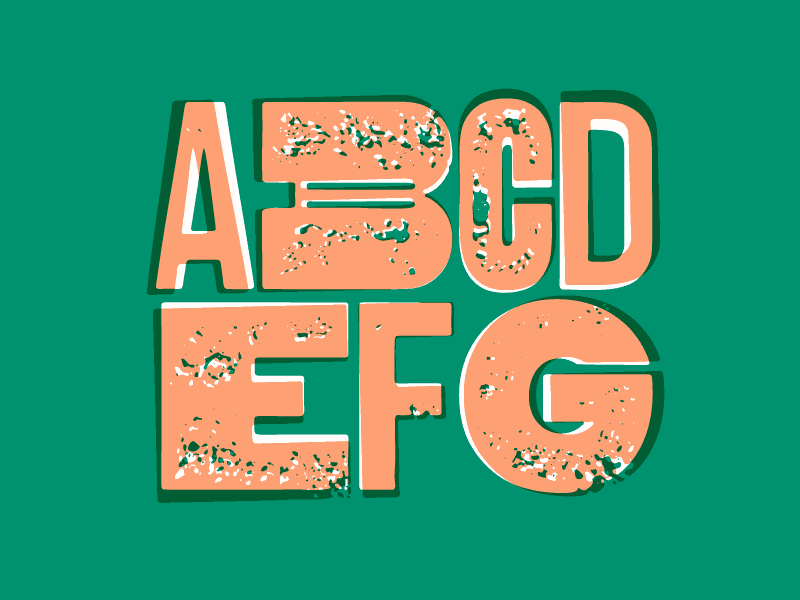
O písme
Písmový systém inšpirovaný drevenými matricami a drevotlačou.
Woodkit Reprint je kapitálové, dekoratívne, experimentálne konštruované písmo primárne určené pre použitie v nadpisoch, obsahujúc 6 štýlov.
Podporovanými znakovými sadami písma Woodkit Reprint sú základná latinka, rozšírená latinka, cyrilika a gréčtina, vďaka čomu môže byť písmo použité vo viac ako 109 jazykoch. S celkovým počtom 1150 znakov, základnou sadou sú tabulárne zarovnané číslice doplnené o proporčné zarovnané číslice a proporčné skákavé číslice pre pokročilú numerickú sadzbu. Funkcie ako štandardné ligatúry, špeciálne ligatúry a kontextové varianty umožňujú ďalšie prispôsobenie a zvyšujú celkovú všestrannosť písma.
Písmový systém inšpirovaný drevenými matricami a drevotlačou pozostávajúci z troch rodín —
Solid, Print a Reprint, každá so šiestimi osobitými štýlmi obsahujúcimi rôzne typy abecedy, komponentov a rôznorodých ornamentov.
Z pohľadu estetiky aj funkcie, najdôležitejším dizajnovým znakov Woodkitu je, že každý znak vypĺňa štvorec, a to nielen horizontálne, ale aj vertikálne. Toto je odkaz na materiálnosť skutočných fyzických drevených štočkov. Toto nielenže podnietilo nové a nečakané konštrukčné riešenia znakov, ale zároveň dodalo hotovému písmu vysokú všestrannosť, vzájomnú zameniteľnosť štýlov, mnoho vizuálnych nápadov nedostupných v proporčných písmach a čo je najdôležitejšie — hravosť. Niektoré štýly a tvary sú priamo inšpirované písmenkami a kockami pre deti. Preto používať Woodkit neznamená iba písať, ale aj stavať a budovať.